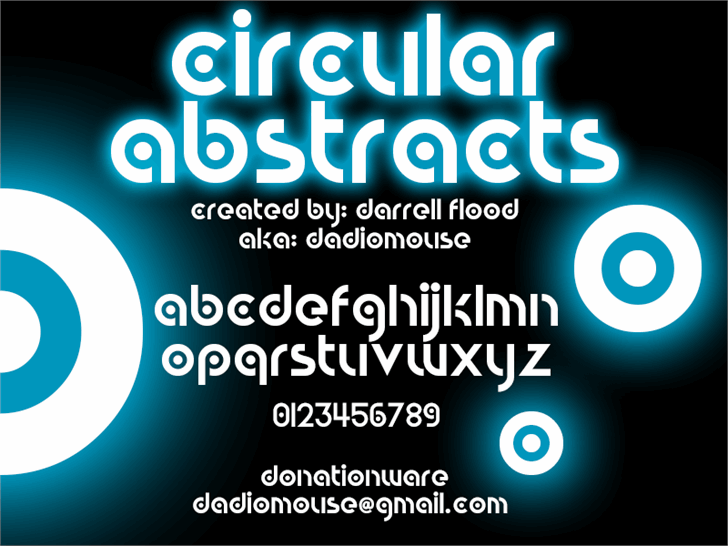
Circular Abstracts Font – Download Grátis
A Circular Abstracts Font é uma tipografia de display criada pelo designer Hamilton usando High Logic FontCreator de Darrell Flood. Essa fonte está disponível gratuitamente para uso pessoal, com a menção explícita de apreciar doações independentemente do valor. Com suas linhas elegantes e formas redondas, esta fonte convida a criar designs criativos e minimalistas que se destacam em qualquer projeto visual. Seu design circular faz dela uma escolha ótima para gráficos de alta visibilidade ou elementos de design digital como ícones e botões interativos. Para os amantes do design e da arte, esta fonte é um recurso valioso capaz de tornar qualquer layout mais atrativo.